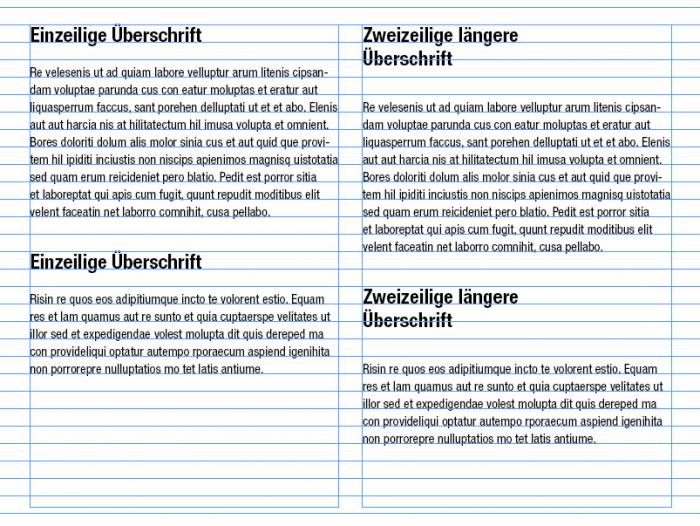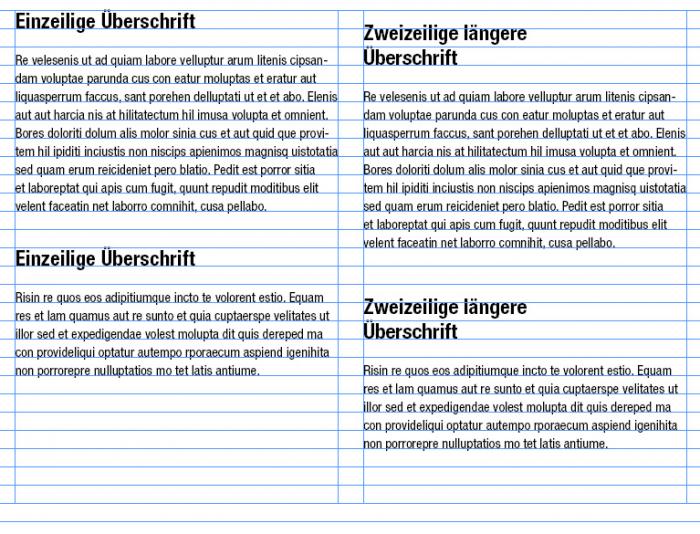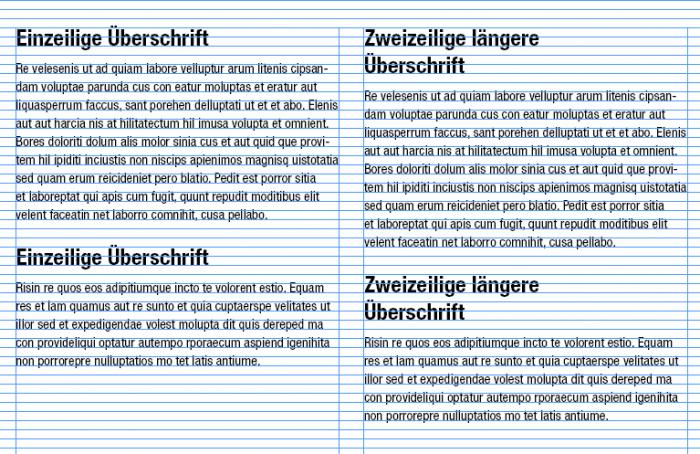
Rasterhaltigkeit bei mehrzeiligen Headlines?
wie im Beispiel zu sehen, arbeite ich gerade an einem Projekt auf dem es auf einer Seite sowohl einzeilige als auch mehrzeilige Überschriften gibt. Habe ich ein Brett vorm Kopf oder lässt sich das Problem nicht anders lösen als durch unterschiedliche Abstände zum Fließtext (wenn ich den Überschriften nicht den gleichen ZAB geben möchte)?
Genau so ist es. Wenn der Fließtext auf der Grundlinie stehen soll, musst du mit unterschiedlichen Abständen leben. Schöner wäre wahrscheinlich, die Überschriften ins Grundlinienraster zu bringen (durch Verkleinern oder Vergrößern), das hängt aber immer vom Projekt ab.
Es ist sicher besser, den zusätzlichen Raum oberhalb der Überschrift zu verklappen als unterhalb.
Ist es das?
Ich dachte schon ich mache vielleicht irgendeinen Denkfehler.
Pachulke: Wenn ich deinen Rat richtig verstehe, sähe es so aus?
Als Norddeutscher, mit maritimem Sachkundeunterricht schon in der Grundschule konfrontiert, frage ich mich, warum ich erst jetzt erfahre, dass die Abstäde auf hoher See entsorgt werden müssen ...
Aber wenn ich das Ergebnis sehe ... nein, das kann so nicht sein  ;-)
OK – jetzt mal eine Grundsatzfrage. Wenn es um ein Buch ginge würde ich diese Frage nicht stellen. Da es hier aber um einen Leporello geht und die Spalten quasi durch die Falz getrennt sind: Was ist sinnvoller?
1. Der Fließtext ist rasterhaltig, aber die Überschriften haben unterschiedliche Abstände zu diesem.
2. Der Fließtext ist nicht rasterhaltig, dafür herrschen aber überall die gleichen Abstände.
Ich würde
3.  Der Fließtext ist rasterhaltig, die Überschriften werden durch Vergrößern oder Verkleinern ins Raster eingepasst
präferieren.
Ich würde
3.  Der Fließtext ist rasterhaltig, die Überschriften werden durch Vergrößern oder Verkleinern ins Raster eingepasst
präferieren.
Das würde ich eigentlich auch.
Ich habe es ausprobiert, doch die vergrößerten Überschriften erschlagen alles und die verkleinerten scheinen mir zu dezent zu sein. :-?
OK – jetzt mal eine Grundsatzfrage. Wenn es um ein Buch ginge würde ich diese Frage nicht stellen. Da es hier aber um einen Leporello geht und die Spalten quasi durch die Falz getrennt sind: Was ist sinnvoller?
1. Der Fließtext ist rasterhaltig, aber die Überschriften haben unterschiedliche Abstände zu diesem.
2. Der Fließtext ist nicht rasterhaltig, dafür herrschen aber überall die gleichen Abstände.
Das ist nicht nur eine Grundsatzfrage, sondern eine Glaubensfrage. Ich neige in solchen Situationen eher dazu, auf die Registerhaltung zu pfeifen, aber das sehen einige Kollegen hier ganz anders.
Ist es das?
Wenn ich deinen Rat richtig verstehe, sähe es so aus?
Eindeutig ja. Das ist nicht nur eine ästhetische, sondern auch eine logische Frage. Die Überschrift steht ja nicht zwischen den Texten, sondern gehört jeweils zum folgenden Text, deshalb sollte der Abstand zu diesem auch fix sein, damit diese Einheit optisch nicht gestört wird. Ist etwas auszugleichen, dann vorzugsweise zwischen den Blöcken, also zwischen Fließtextende und Überschrift des nächsten Abschnittes.
Mal probiert, Dein Grundlinien-Raster noch einmal zu teilen, damit Du etwas flexibler arbeiten kannst?
Du meinst so? Das sich die Zeilen irgendwann wieder "synchronisieren"?
Im Prinzip ja. Aber der Fließtext sollte immer synchron sein. Dies wiederum bedeutet in Deinem Fall in der rechten Spalte mehr Abstand nach der Überschrift (hatte ich vorhin leider nicht auf dem Zettel … denn wie Pachulke schon anmerkte, ist das ja nicht so elegant, aber eine andere Lösung fällt mir dann gerade auch nicht ein).
Moin!
Als Norddeutscher, mit maritimem Sachkundeunterricht schon in der Grundschule konfrontiert, frage ich mich, warum ich erst jetzt erfahre, dass die Abstäde auf hoher See entsorgt werden müssen ...
Es wurde schon so viel Zeugs in die Nordsee veklappt, an das wir uns besser bei der nächsten Fischstäbchenmahlzeit nicht erinnern wollen, dass ein Veklappen von Leerräumen zur Abwechslung mal eine Wohltat wäre! ;-)
Pachulkes Logik ist auf jeden Fall korekt. Das 2. Bsp. sieht dennoch besch...eiden aus.
Wie sähe das ganze aus, wenn man im 3. Bsp. den Boden des Klappschiffes zwischen den beiden Zeilen der Überschift öffnet und dort noch 'nen zusätzlichen halben Grundtextzeilenabstand verklappt? ;-)
die Überschriften werden durch Vergrößern oder Verkleinern ins Raster eingepasst
Das scheint mir keine gute Lösung zu sein. Die Formatierung von Überschriften ist ja nicht beliebig, sondern hat einen Bezug zum Inhalt (z.B. hierarchische Abstufung bei mehreren Überschriften). Und außerdem sollte ja die Formatierung in sich stimmig sein. So würde man ja sicherlich auch im normalen Fließtext nicht eine Zeile in der Schriftgröße verändern, nur damit der Umbruch besser passt. Ich sehe keine ausreichende Rechtfertigung dafür, bei Überschriften davon abzuweichen.
Die halben Grundlinienschritte finde ich auch keine elegante Lösung, weil dann die Grundlinie der Überschrift um eine halbe Höhe versetzt ist.
Jo. Wurde auch eher mal zum Experimentieren vorgeschlagen. (Erfahrungsgemäß kann es aber ganz nützlich sein, um einen optischen Bezug der Oberkante von auf dem Raster mit laufenden Abbildungen zum Fließtext herzustellen, aber dies nur am Rande, weil nicht das Thema.)
Ansonsten bin ich natürlich absolut bei Dir und sehe auch immer zu die Headlines auf dem normalen Raster zu bezwingen ; )